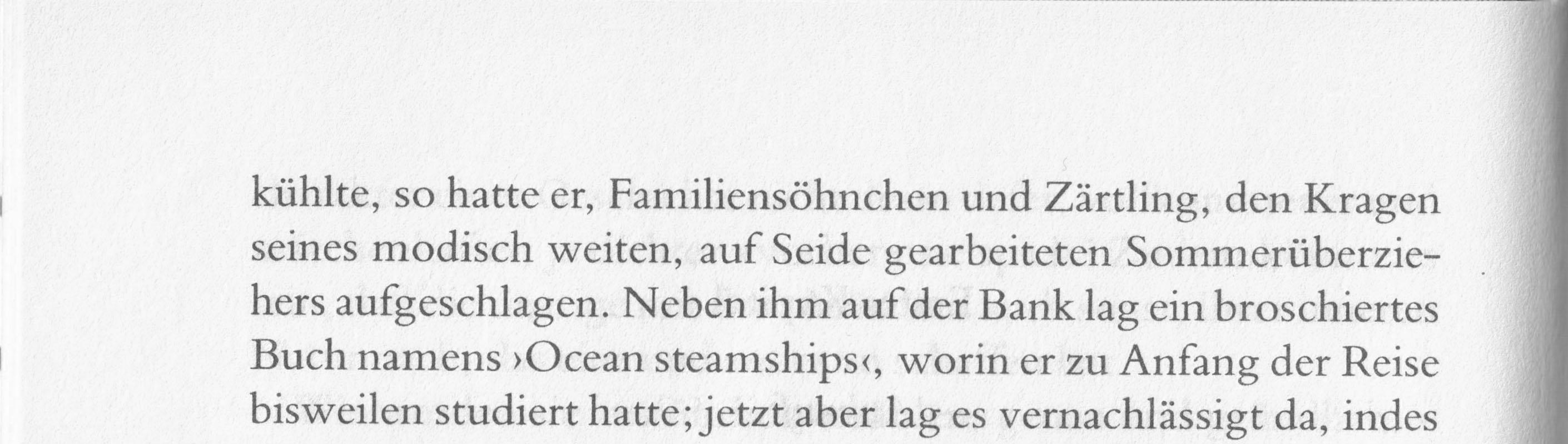
Suche Schrift dieser Suhrkamp-Buchseite aus 2015 (Thomas Mann: Der Zauberberg)
Eine Bembo käm mir da in den Sinn …
Ich habe den Text in Bembo nachgesetzt, aber in meiner Version hat die Bembo ein ausladenderes »R«. Ich verwende eine Bembo-Version von Adobe (siehe 2. Screenshot).
Monotypes Bembo Book Pro hat ein in der Breite etwas kompakteres /R als Alternativzeichen.
Nachtrag: auch Adobes Bembo Std hat dieses alternative /R.